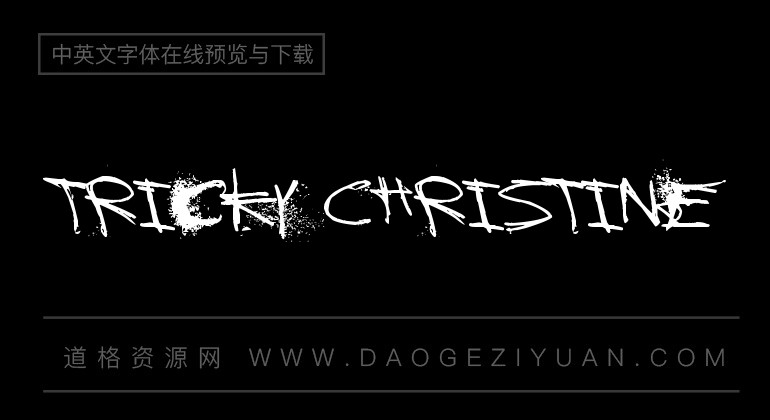
? Tricky Christine 字体是一款拥有轻松、活泼、清新风格的英文字体,主要用于文章标题、报纸标题、海报标题、书籍标题等,能够给读者带来活力和快乐。Tricky Christine 字体有着粗细错落的设计,每个字母都有着独特的设计,能够给读者带来更多的视觉冲击。内容介绍
Tricky Christine是一款非常不错的手写艺术字体,具有很好的视觉感,适合于文化类的宣传设计、商业类品牌的广告和产品包装设计以及个性化文字排版等较多场景。